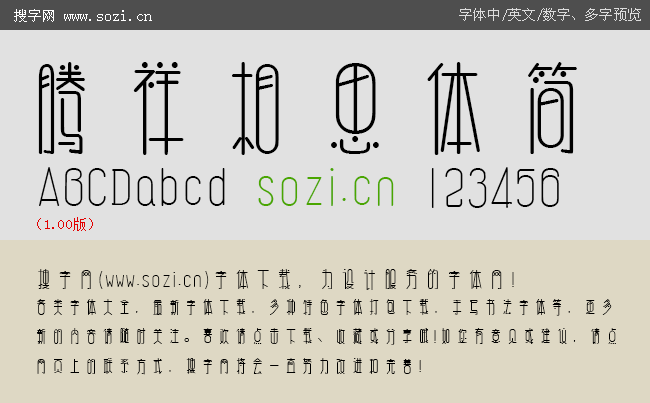
騰祥相思體簡(jiǎn)1.0
搜字網(wǎng)給大家提供一款騰祥相思簡(jiǎn)體中文字體下載。騰祥相思簡(jiǎn)是一款應(yīng)用于藝術(shù)設(shè)計(jì)方面的中文簡(jiǎn)體漢字,該字體筆畫纖細(xì)精致、簡(jiǎn)潔清晰,每個(gè)字風(fēng)格統(tǒng)一,可應(yīng)用于平面設(shè)計(jì)、出版印刷、廣告設(shè)計(jì)、包裝設(shè)計(jì)等領(lǐng)域。